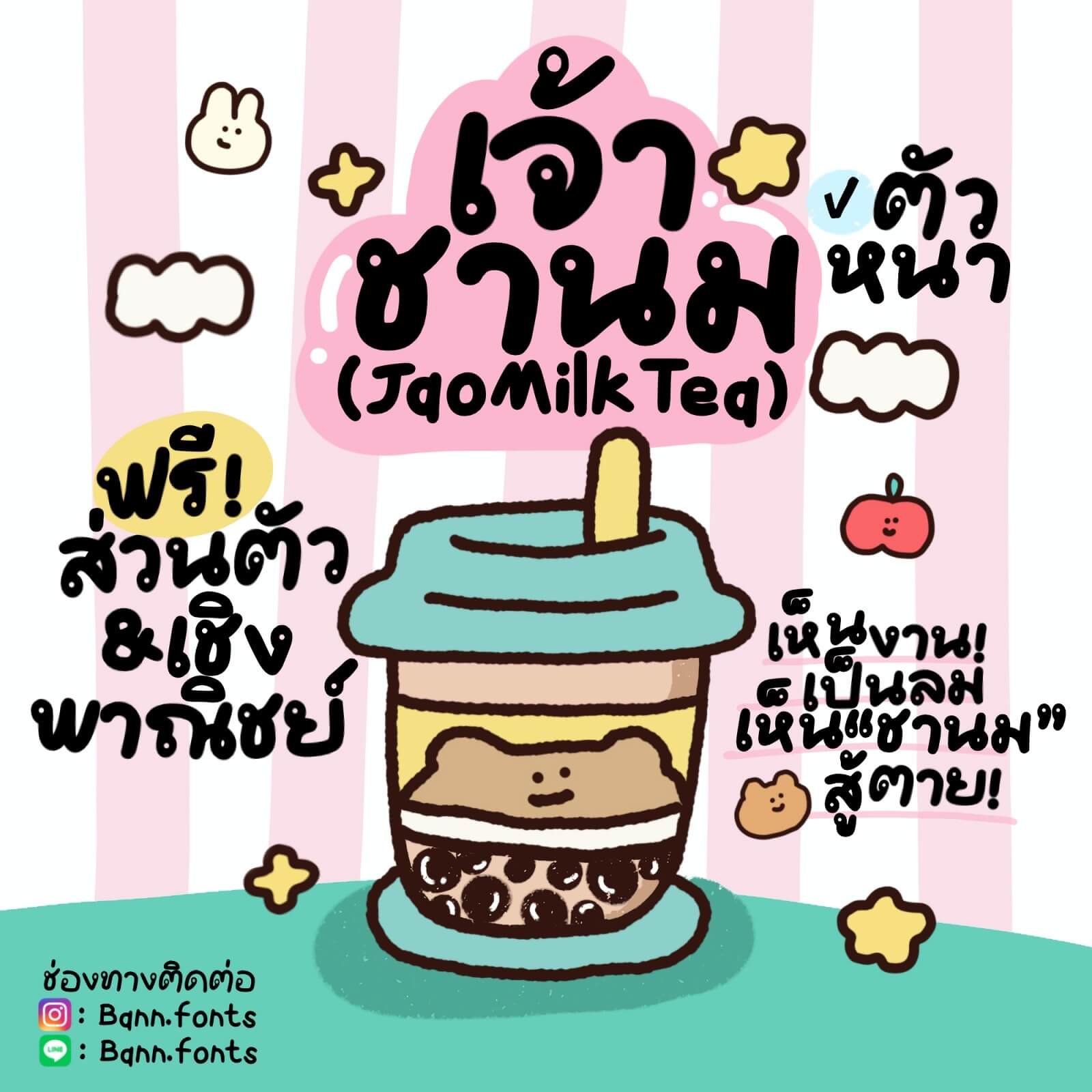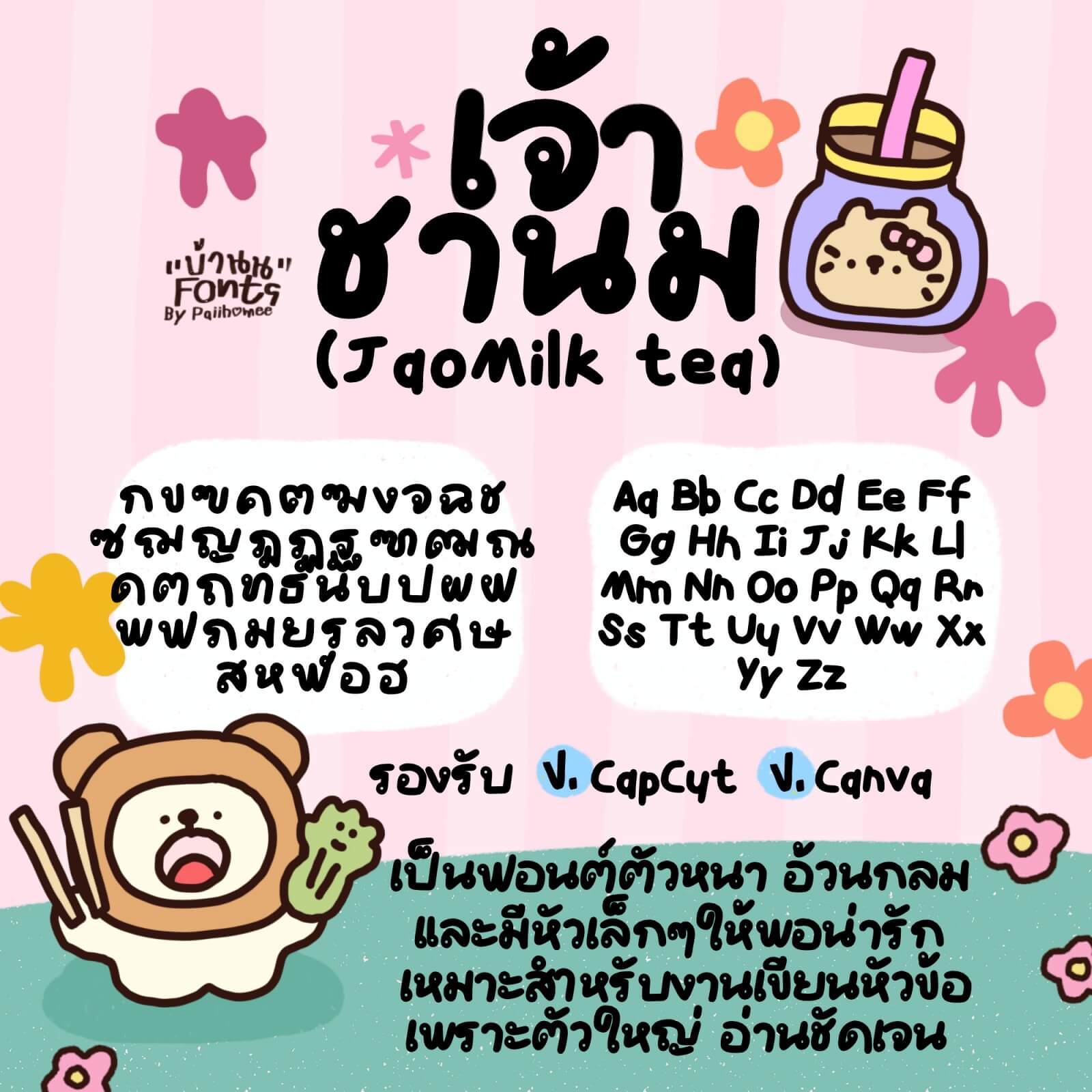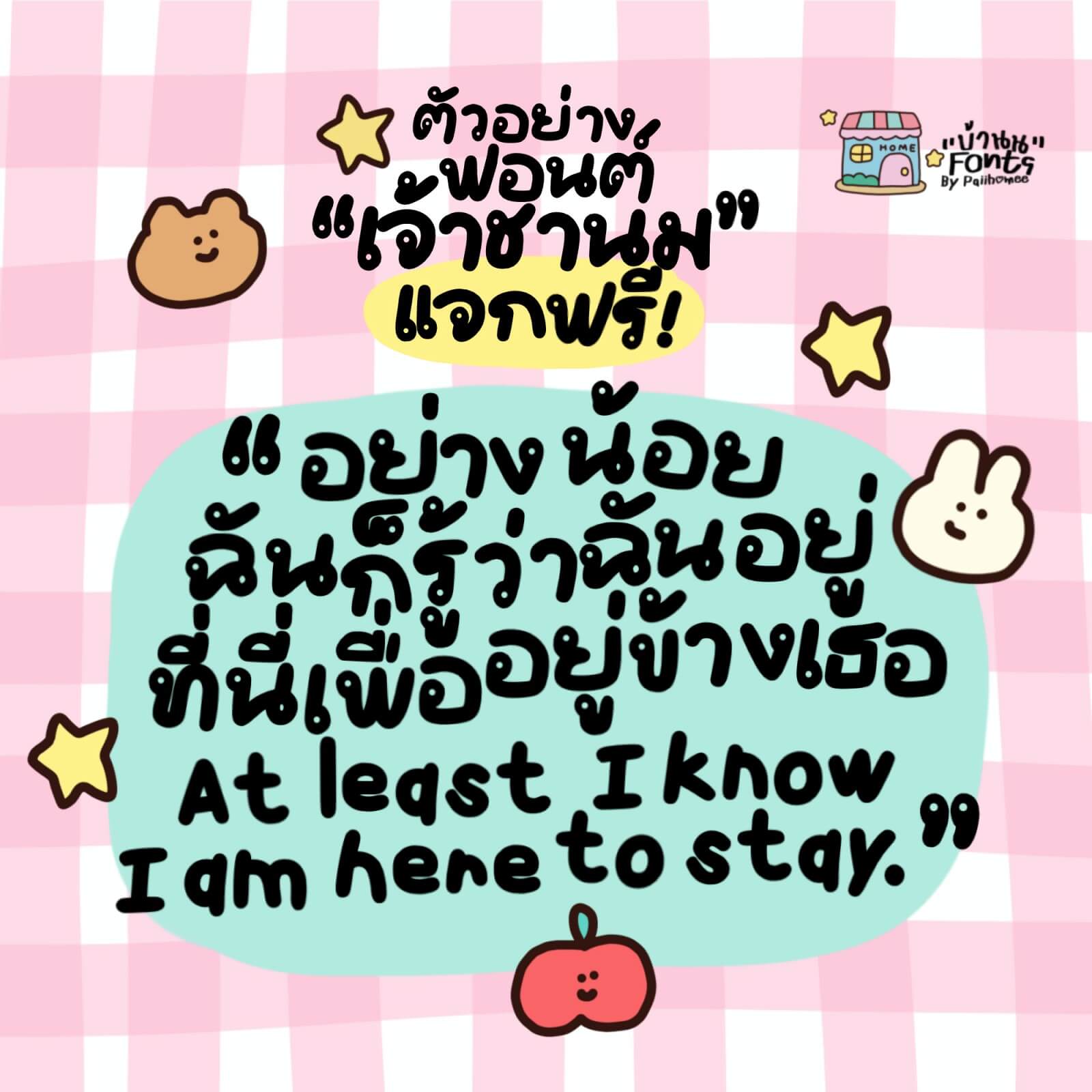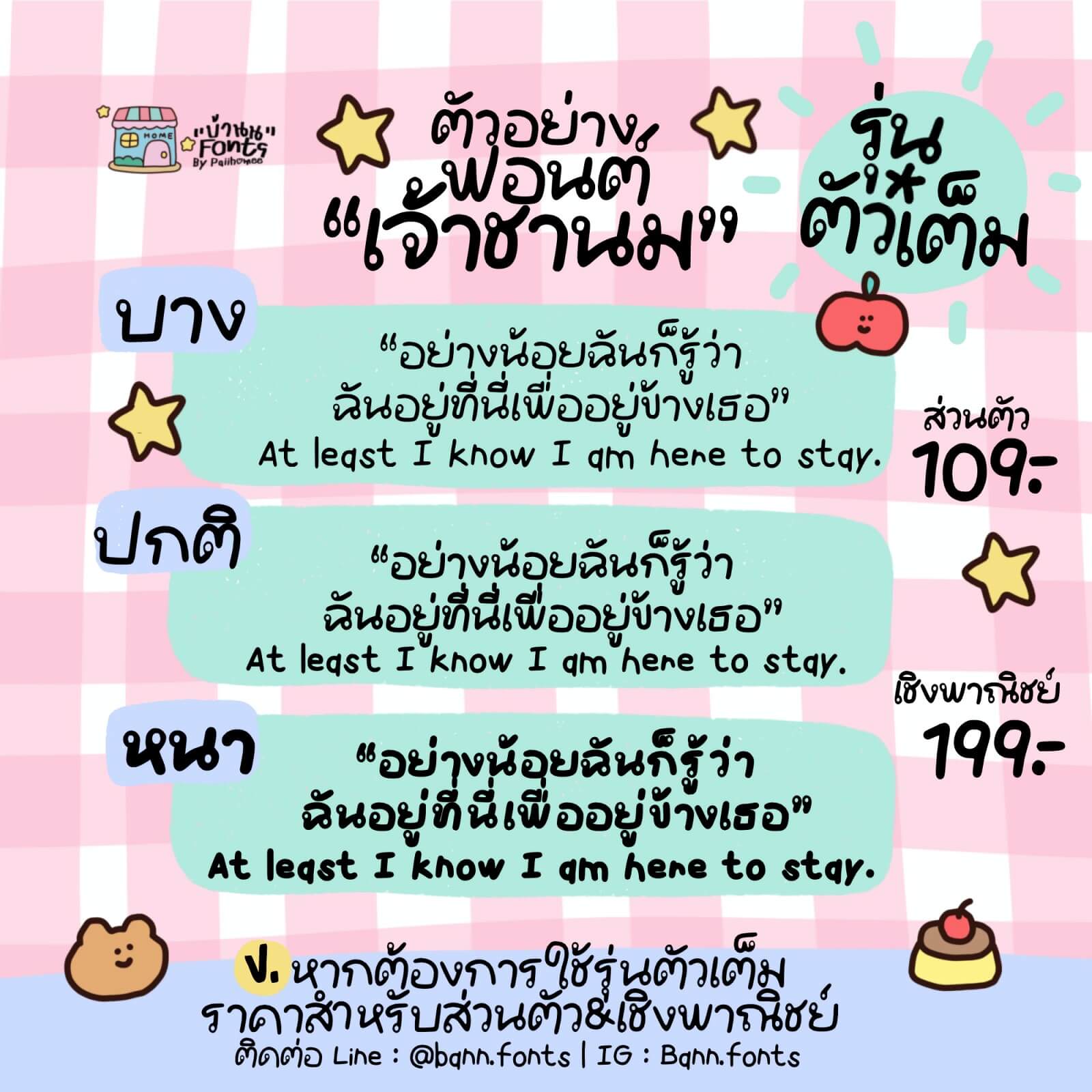
ฟอนต์เจ้าชานม JaoMilk Tea (ตัวหนา) – แจกฟรี! สำหรับใช้ส่วนตัว & เชิงพาณิชย์ ฟอนต์ตัวอ้วนกลม หัวเล็กปุ๊กปิ๊ก
เรียบร้อย อ่านง่าย เหมาะสำหรับเขียนหัวข้อหลัก เช่น ทำคลิป แต่งปกรูป เพราะตัวใหญ่อ่านชัดเจน โหลดไว้ติดเครื่องไว้เลย แนะนำเลยค่ะ!
เวอร์ชันฟรี จะเป็นรุ่นตัวหนา (พิเศษ)
ส่วนฟอนต์ตัวเต็ม จะมีทั้ง 3 ขนาด (เส้นบาง เส้นปกติ และ เส้นหนา)
เจ้าชานม (JaoMilk Tea)